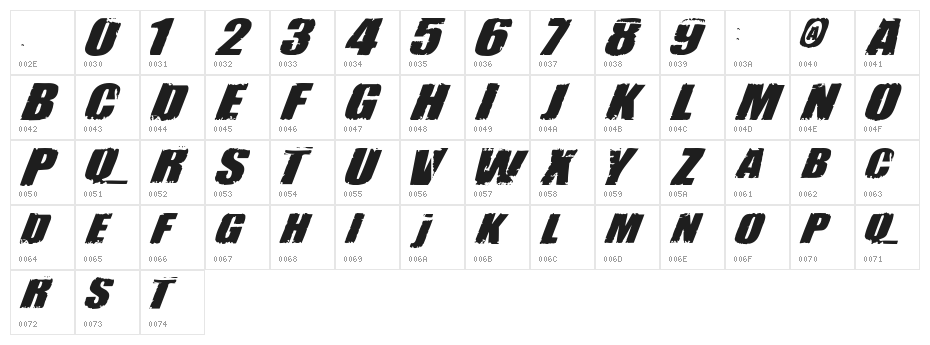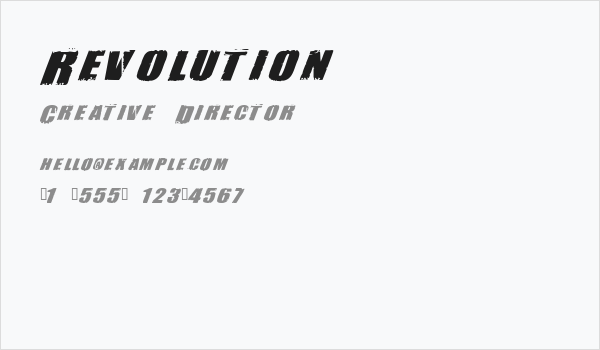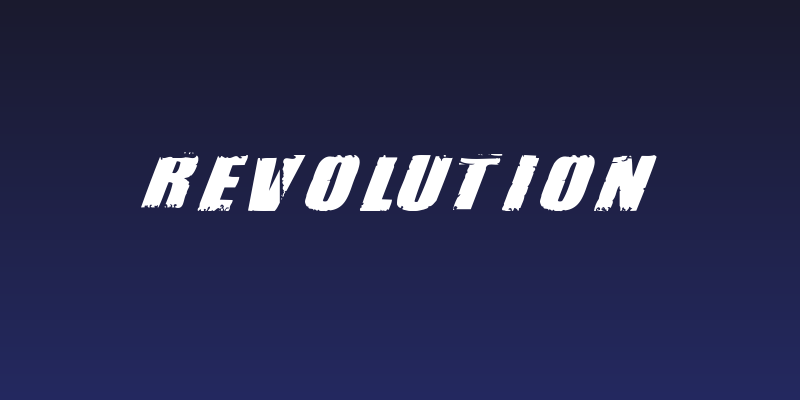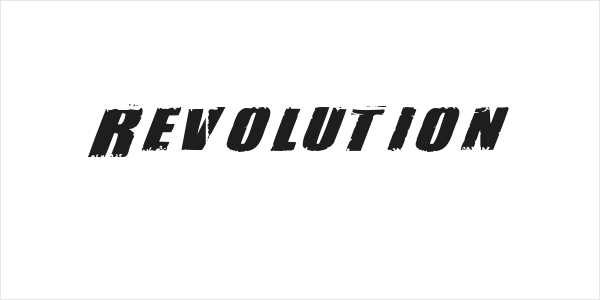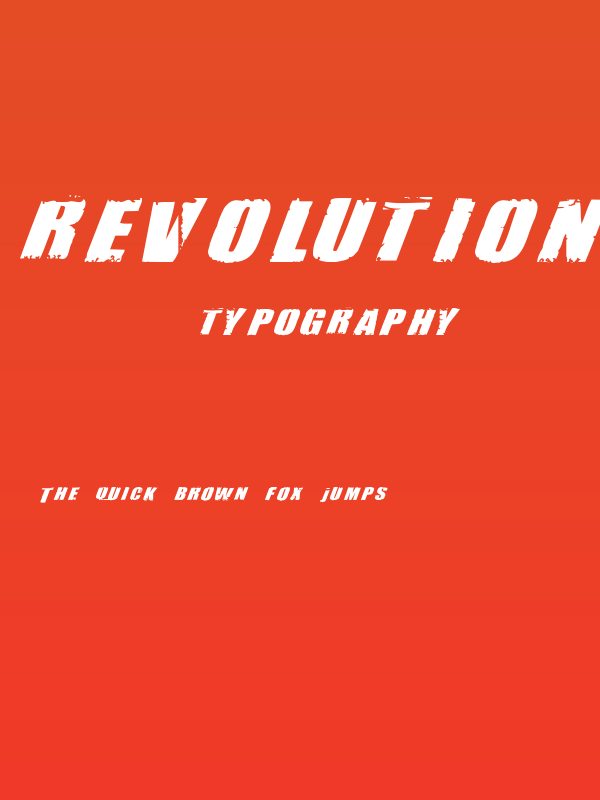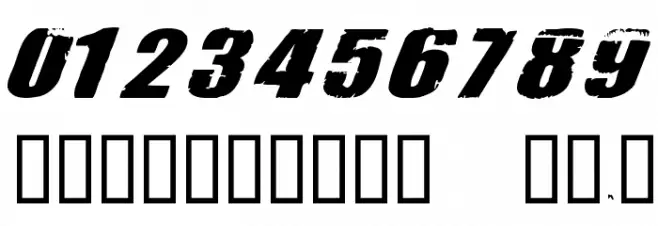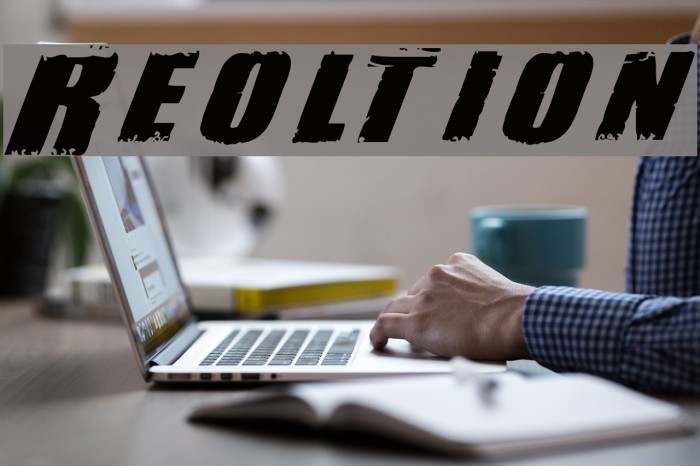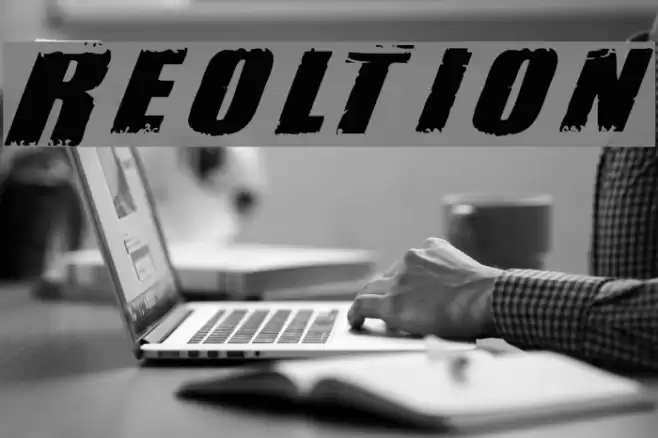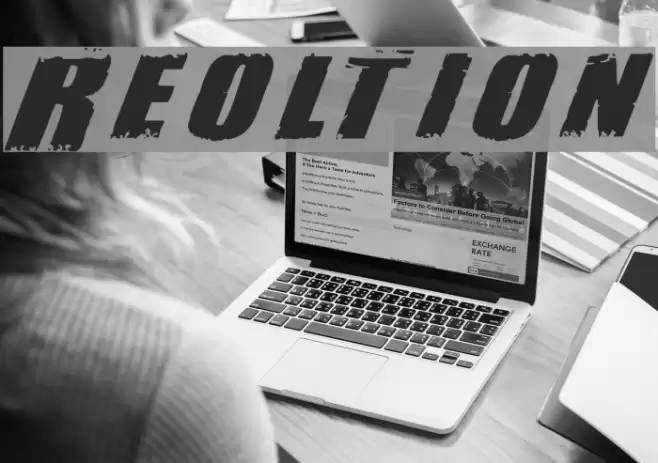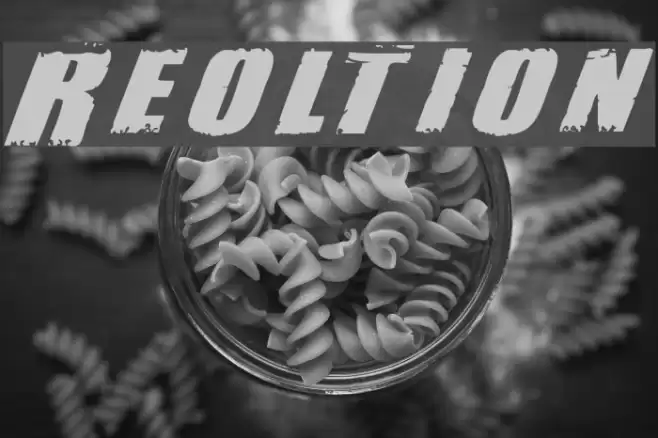
Revolution Font
| カテゴリ | Distorted Eroded |
| 全体的なスタイル | Modern, Urban, Energetic |
| 用途 | Headlines, Posters, Branding |
| おすすめプロジェクト | Ideal for posters, branding, headlines, and any design needing a bold, gritty impact. |